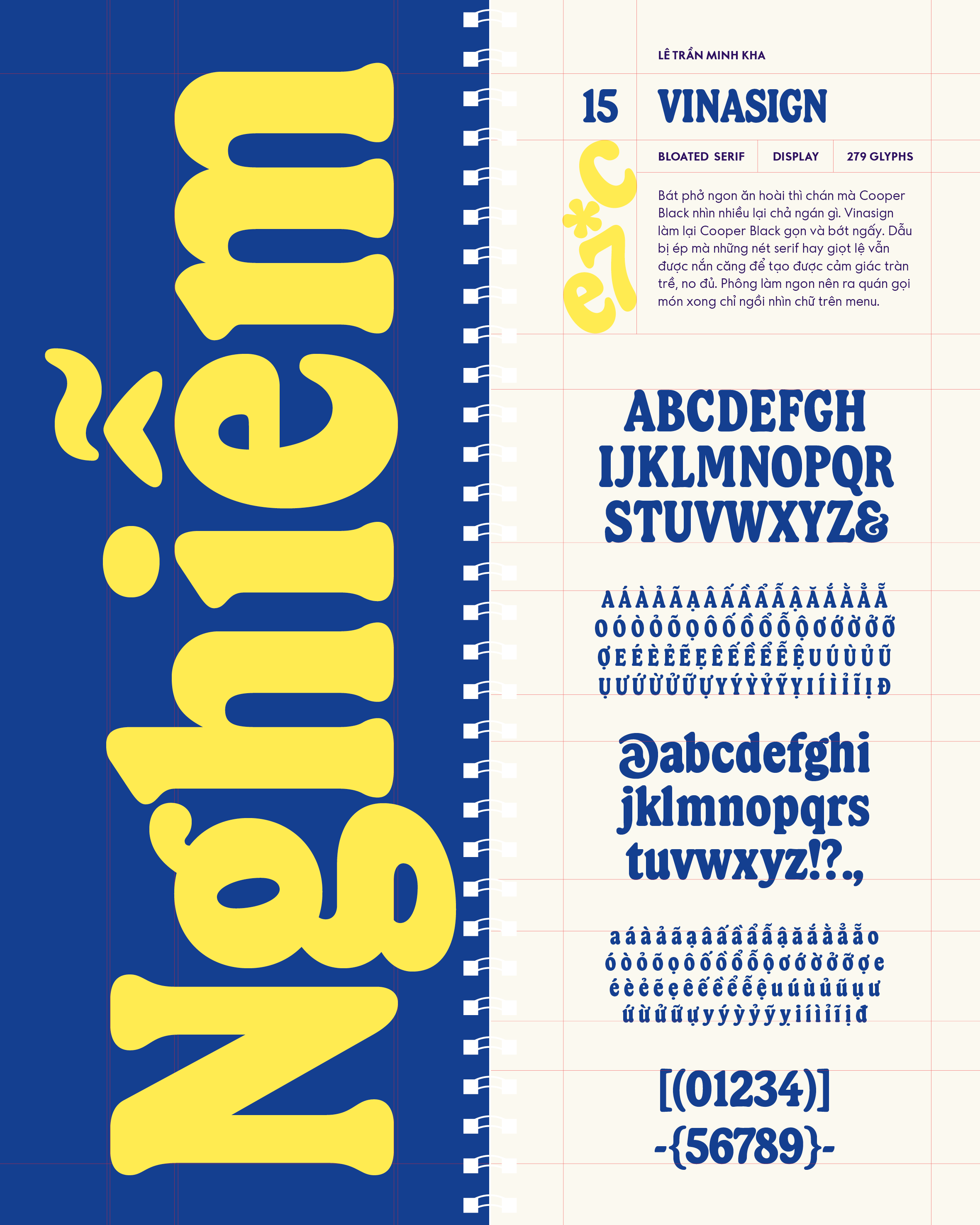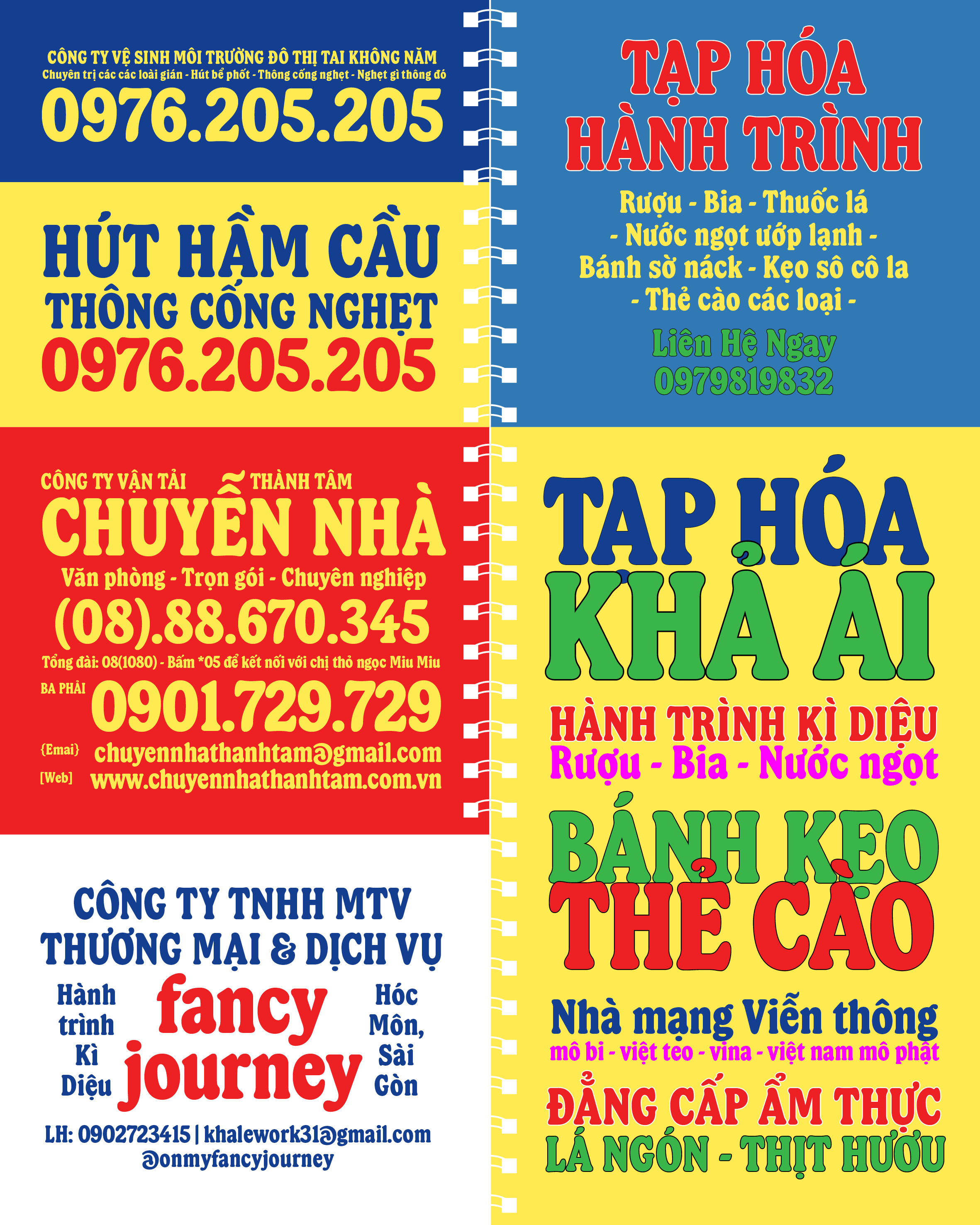
Vinasign
Về Vinasign: Bát phở ngon ăn hoài thì chán mà Cooper Black nhìn nhiều lại chả ngán gì. Vinasign làm lại Cooper Black gọn và bớt ngấy. Dẫu bị ép mà những nét serif hay giọt lệ vẫn được nắn căng để tạo được cảm giác tràn trề, no đủ. Phông làm ngon nên ra quán gọi món xong chỉ ngồi nhìn chữ trên menu.
Bloated Serif
Text
Lê Trần Minh Kha